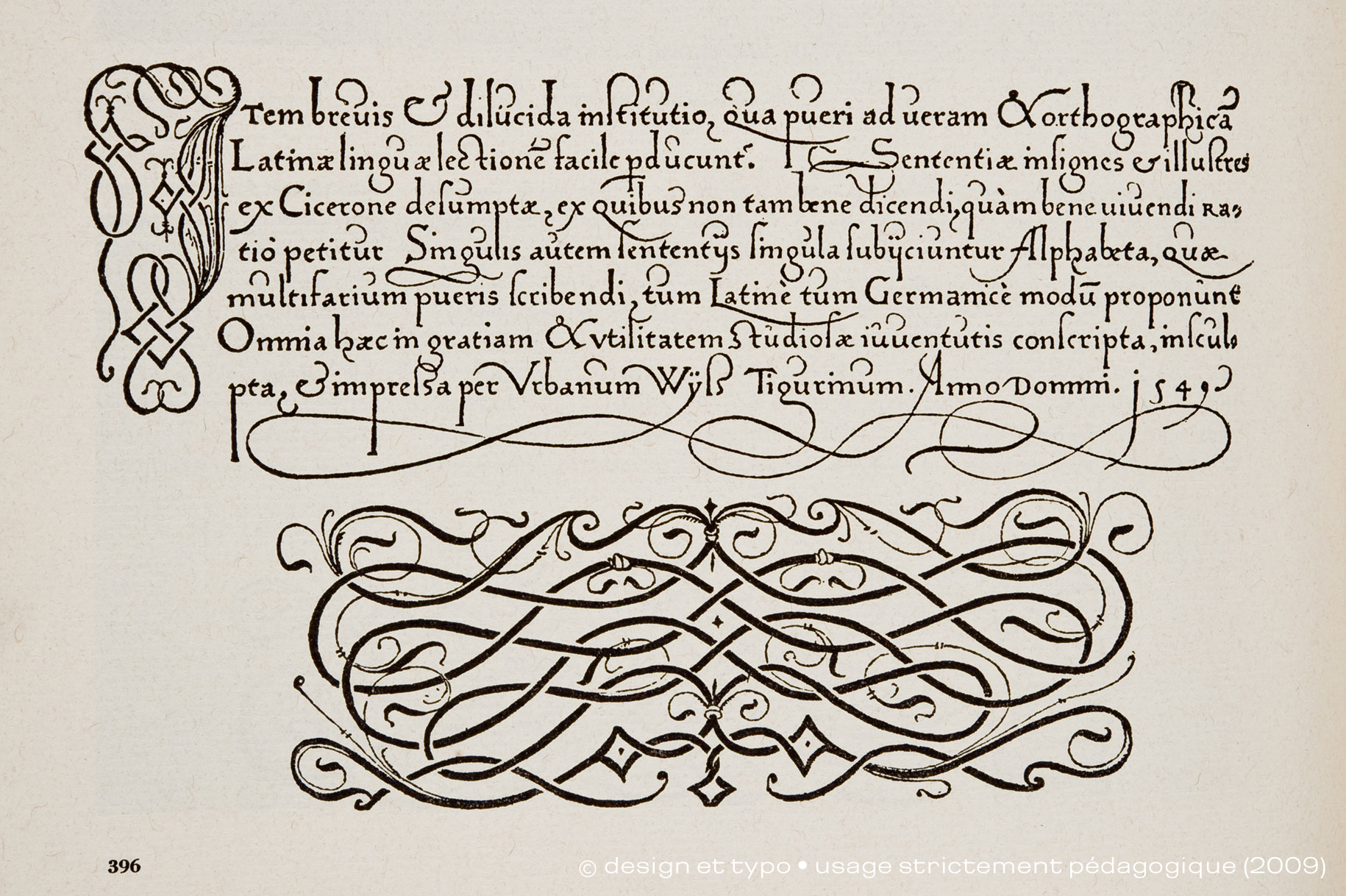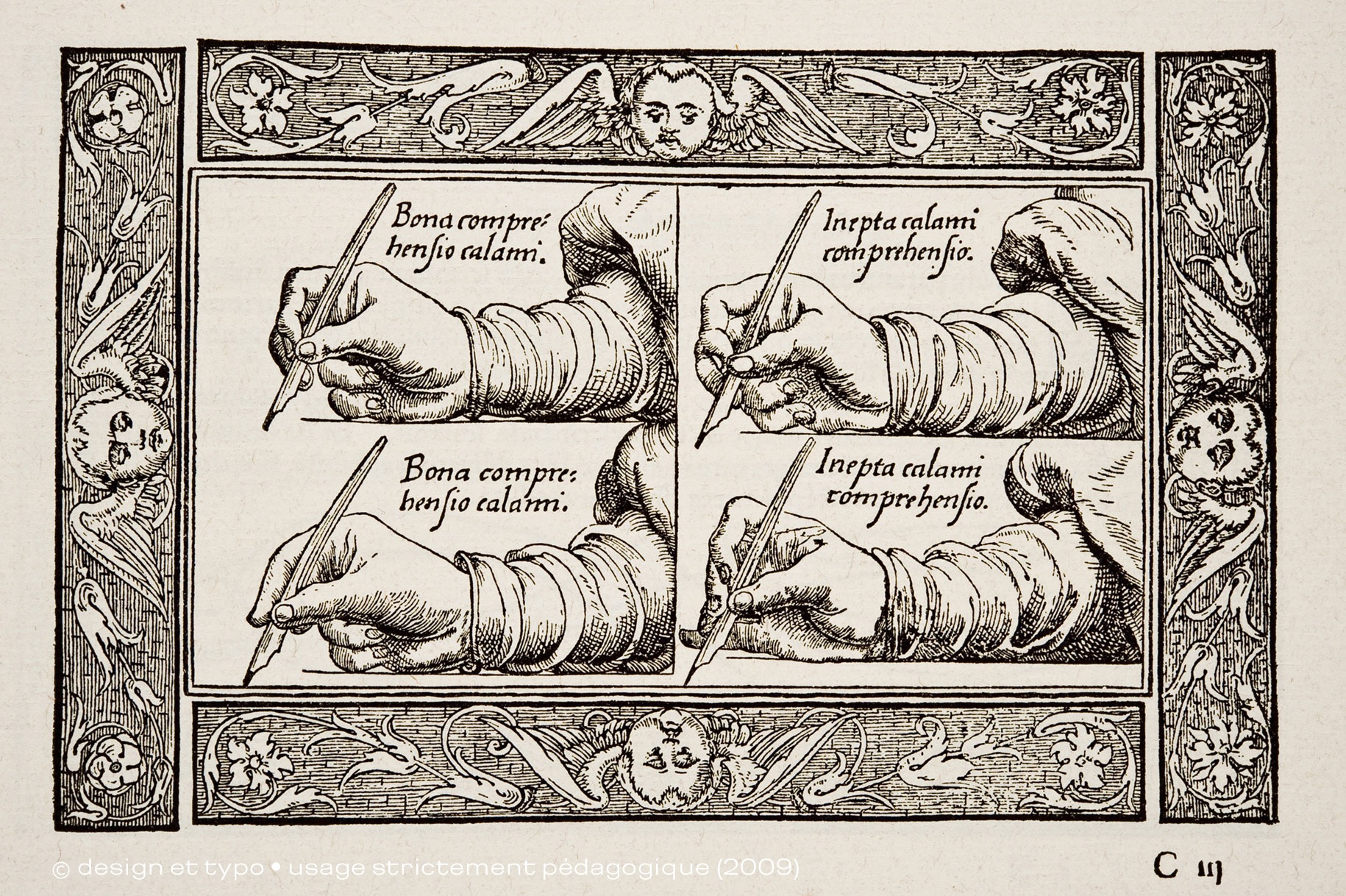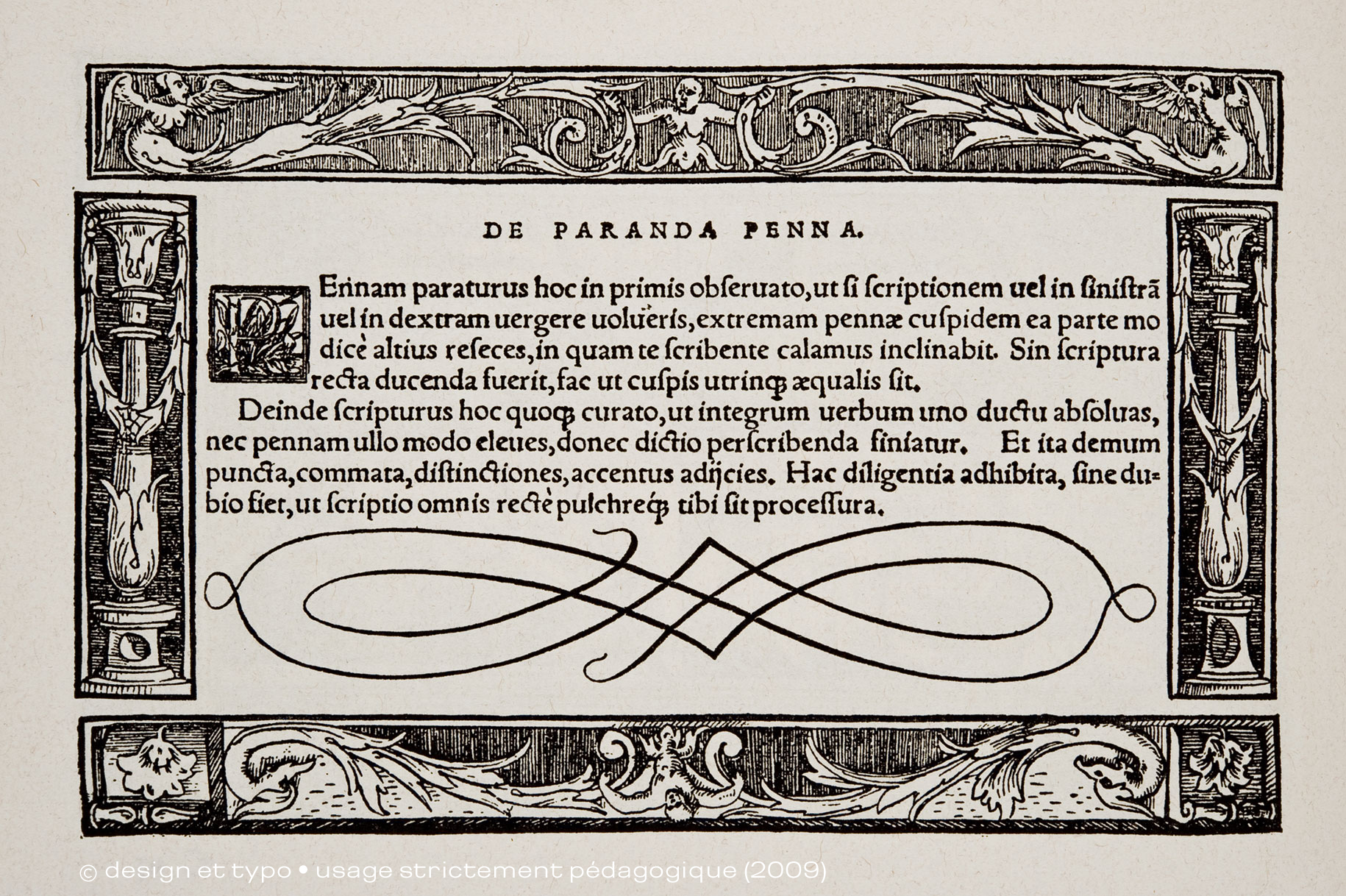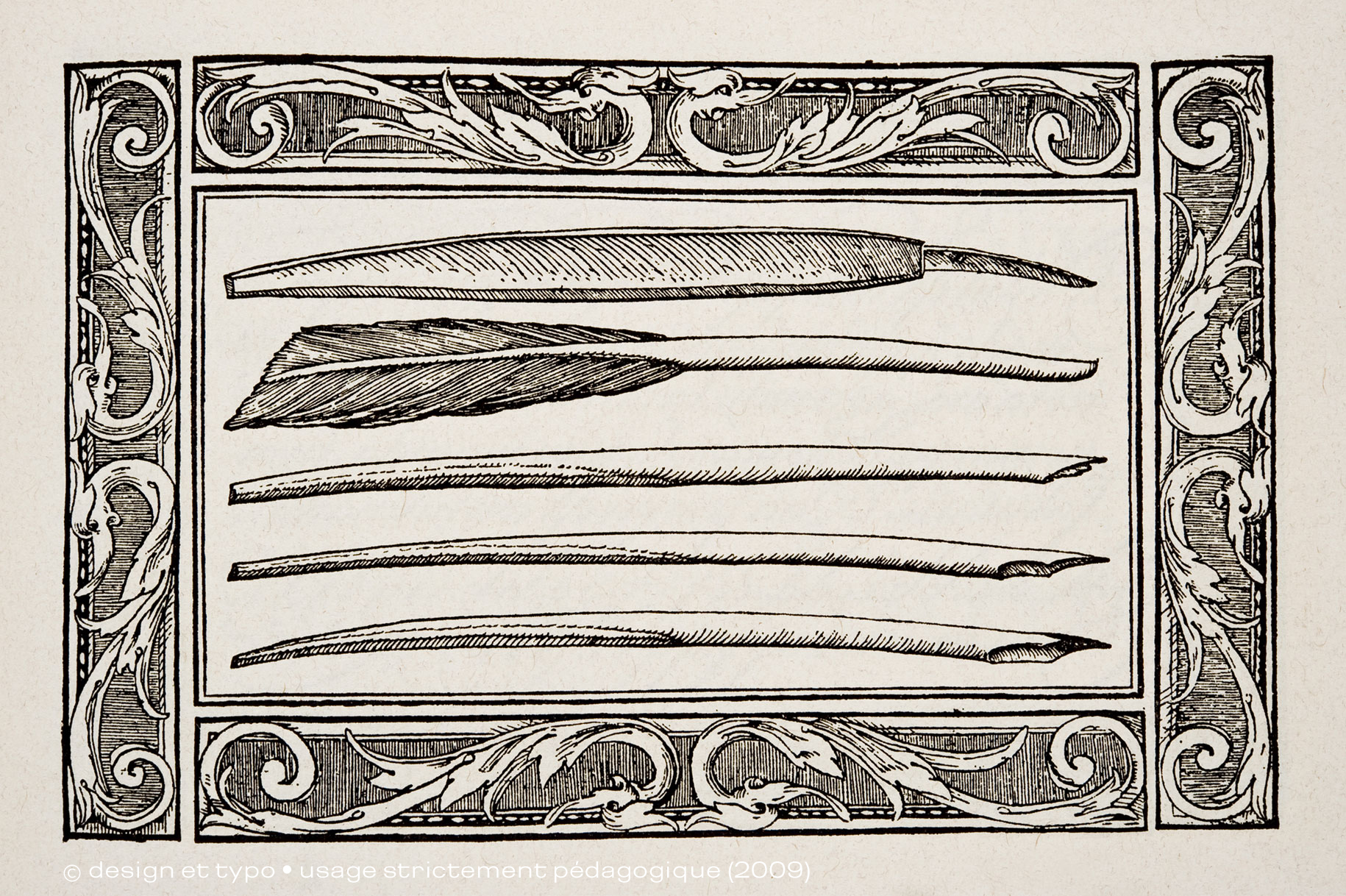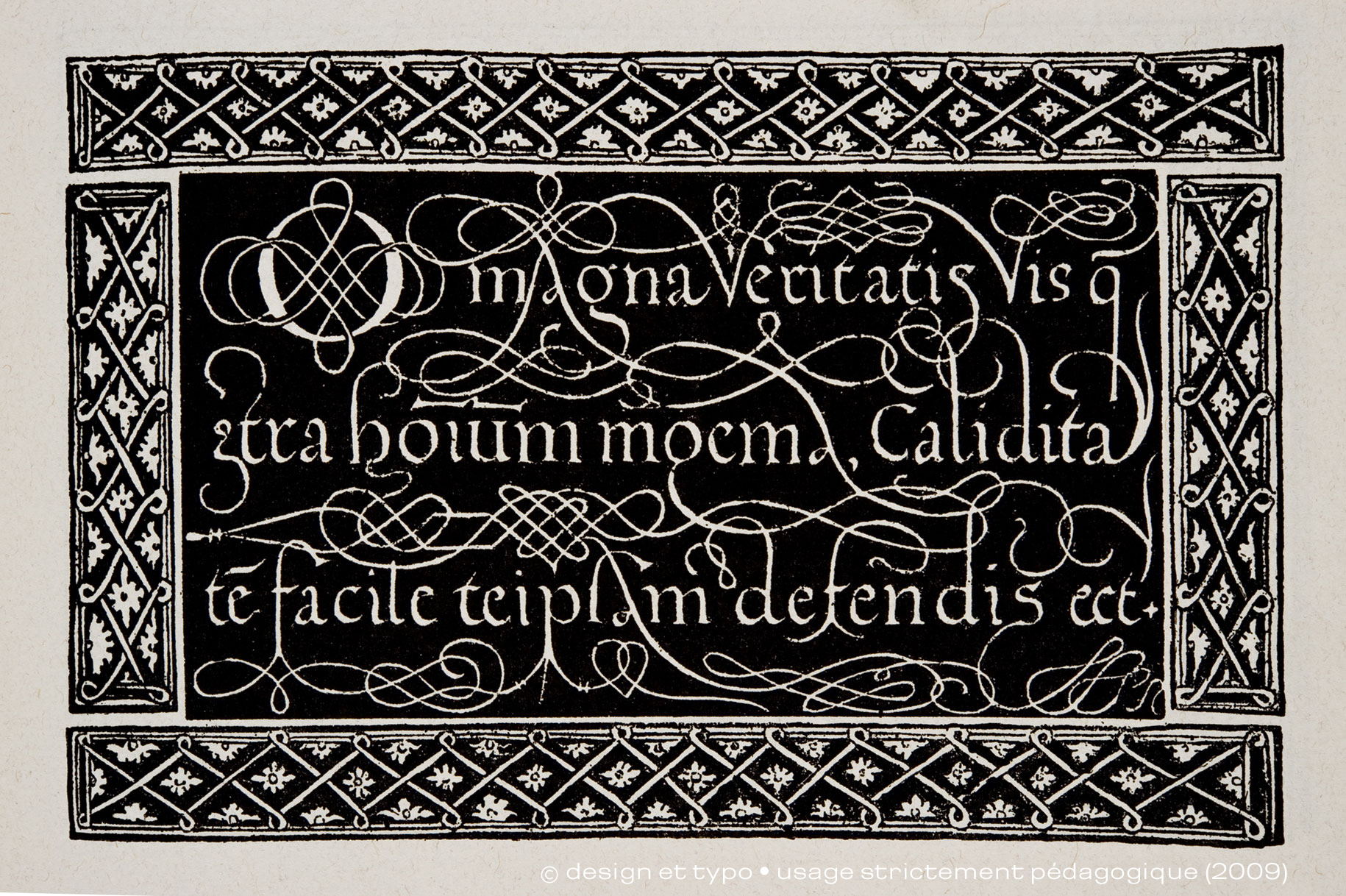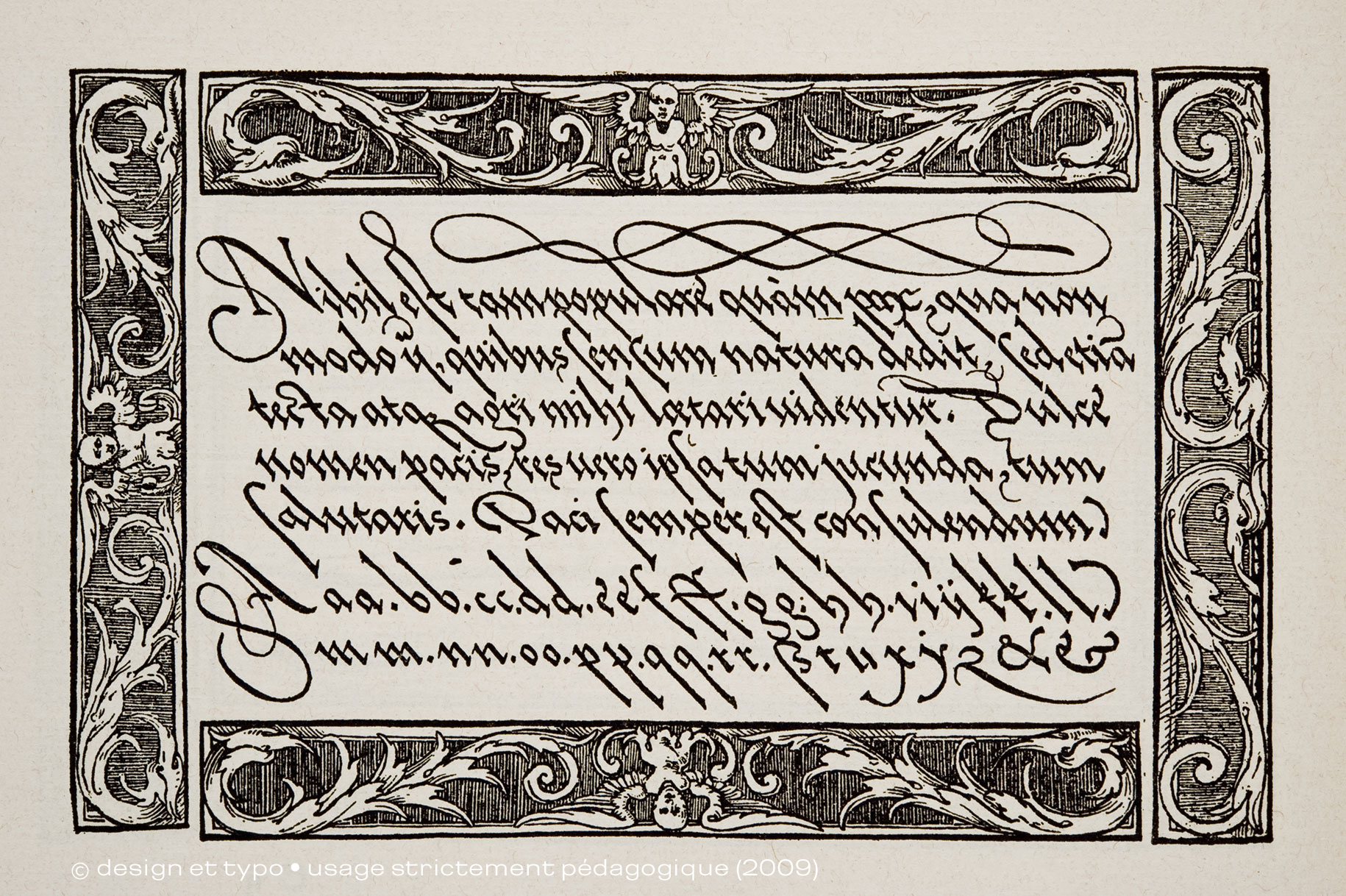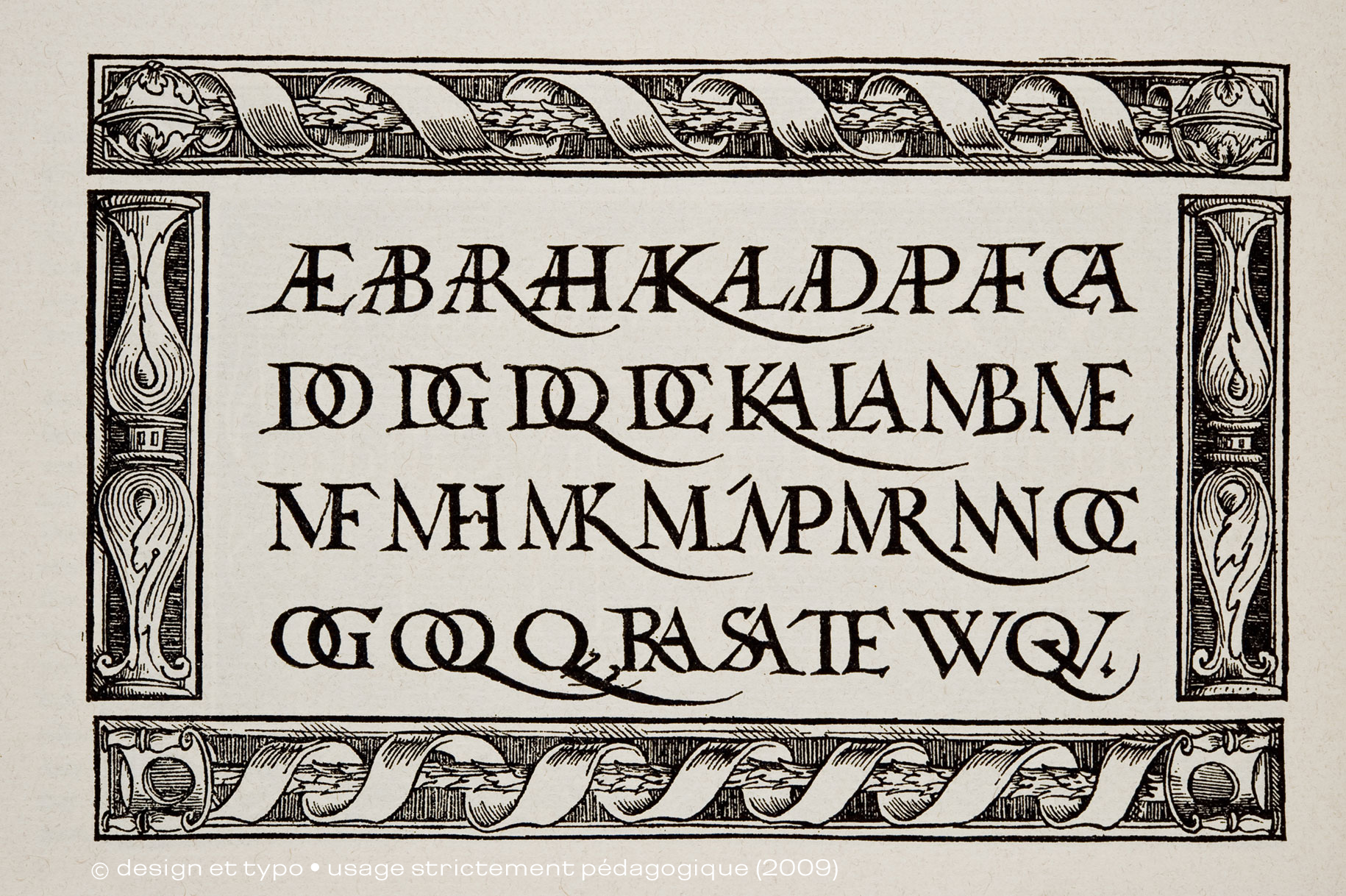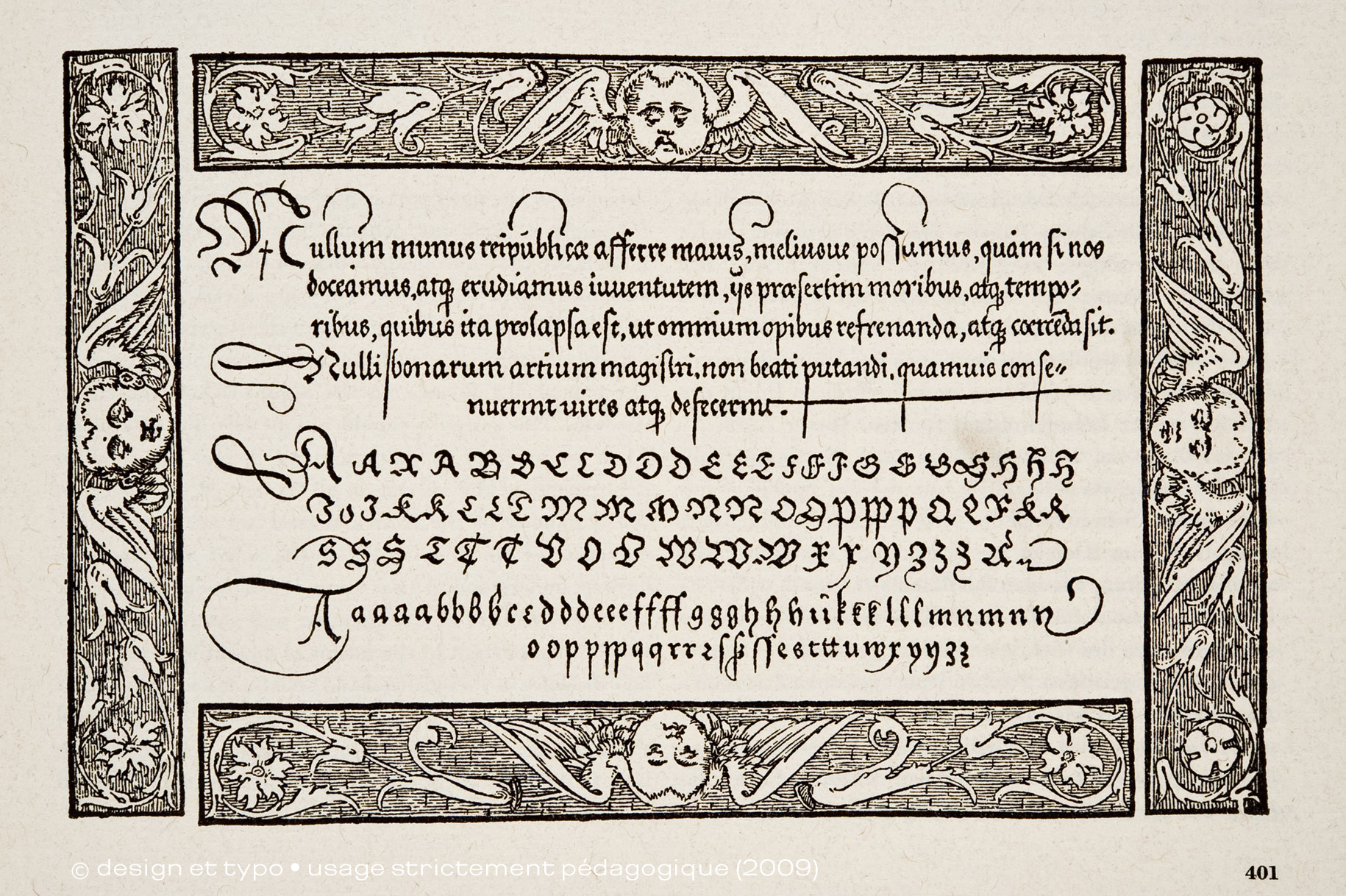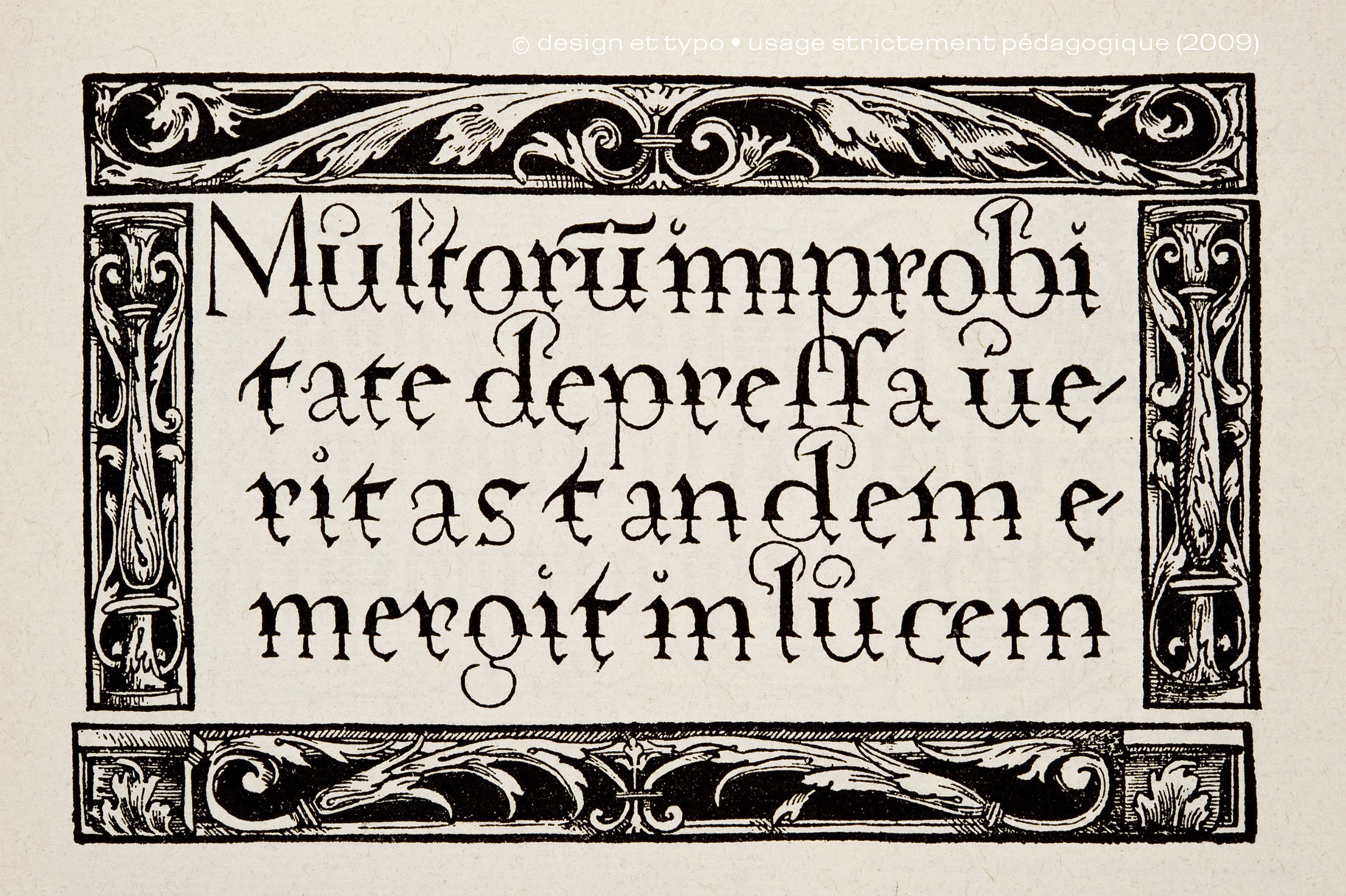
Graphis 1945 | Le processus créatif entre 1945 et 1989 (3/3)
Et en cette année 2009, alors que nous allons bientôt fêter le vingtième anniversaire de l’avènement du monde numérique moderne, nous tenions à design et typo à vous faire partager un certain nombre de documents qui attestent de la vivacité créatrice d’avant le numérique.
Le  «Songe et Mensonge de Franco», une suite de gravures a été créée par Pablo Picasso en 1937.Tout comme le grand violoncelliste Pablo Casals et nombre d’autres artistes, d’écrivains et de savants de sa nation, Picasso s’est efforcé de servir du meilleur de son génie, pendant les tragiques années de la guerre civile espagnole, son pays, son peuple et la cause de la République. C’est ainsi qu’il peignit pour le pavillon espagnol de l’Exposition internationale de 1937, à Paris, l’immense fresque de Guernica, dont la puissance fascina tant de spectateurs venus de tous les pays dumonde.
La même volonté a présidé à la naissance de «Songe et Mensonge de Franco» que l’artiste mit à disposition de l’Office des relations culturelles rattaché à l’ambassade de la République Espagnole, qui put ainsi en assumer la vente au profit de la cause républicaine, dans le cadre de l’Exposition. La publication Graphis de 1945 reproduit le manuscrit des textes rédigés par Pablo Picasso, de même que les 18 gravures et aqua-tinta, groupées sur deux planches en rassemblant chacune 9 et d’un format de 32 cm sur 42, le tout sous une couverture originale dessinée par l’artiste…
Reproduction de deux planches
Fritz Keller et ses décorations
Architecte décorateur et graphiste le jeune zurichois Fritz Keller réalisa ces décorations en 1945 pour la Foire internationale de Barcelone.
Le Traité de Calligraphie d’Urban Wyss
Photos et montages de Pierre Boucher
En regardant ces montages photographiques de Pierre Boucher, nous ne pouvons nous empêcher d’interroger ce passé incroyablement fertile en processus créatif et de nous poser la question: «mais comment faisaient-ils sans Photoshop et Illustrator?». Et la réponse invariablement est la même:: «ils faisaient» de leurs mains associés à l’ingéniosité et à l’intelligence créatrice. Les artistes revendiquaient bien souvent la dénomination d’Homo Faber, «celui qui fait», opposé à celui qui compose la musique ou écrit de la littérature.Bien sûr les techniques existaient: dessin, peinture, huile, aquarelle, gouache, les outils aussi, pinceau, tire-ligne, compas, crayons, plumes, brosses, couteaux. etc.
Et bien sûr certains artistes n’hésitaient pas à s’associer avec des ateliers de sérigraphies ou lithographies sans compter ceux, plus avancés qui allaient directement dans les ateliers offset pour travailler sur des films positifs et négatifs afin d’obtenir des superpositions et incrustations très créatifs. Voyez l’œuvre d’un Bradbury Thomson pour la Westvaco et vous comprendrez mon discours. L’œuvre de Pierre Boucher s’inscrit bien dans ces mélanges de techniques pour donner l’illusion tout en construisant des espaces d’une grande modernité.
Publicité pour des «fournisseurs graphiques» de 1945 à Zurich, Suisse.